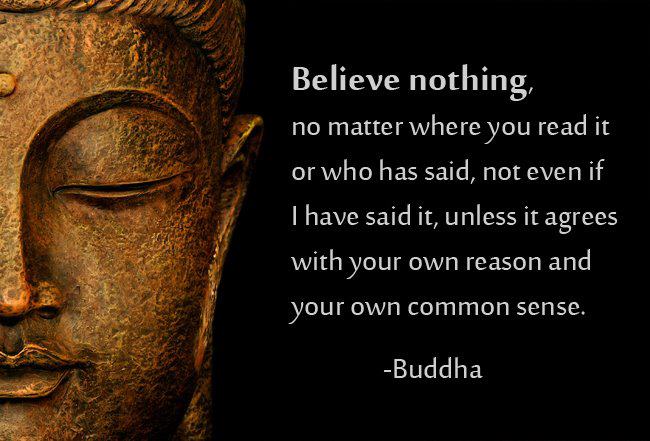
kennt jemand diese Schrift?
Ich finde, sie hat sehr charakteristische Zeichen, wie beispielsweise das "y" - aber ich habe über eine halbe Stunde lang Linotype und Fontshop durchforstet, ohne sie zu finden.
Dabei bin ich mir sicher, dass ich sie auch sonst schon mal wo gesehen habe.